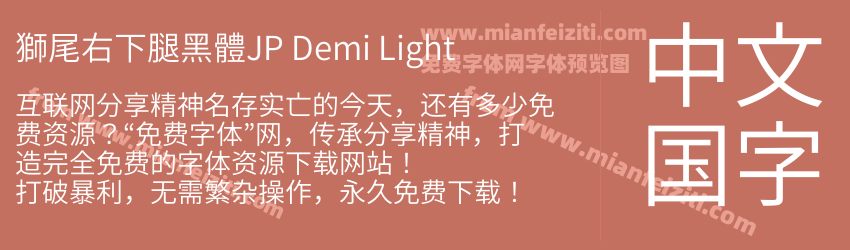
獅尾右下腿黑體JP Demi Light
字体名称: 獅尾右下腿黑體JP Demi Light
Postscript名称: SweiRightBottomLegCJKjp-DemiLight
字体版本: Version 2.130
字体字重: DemiLight
本款“獅尾右下腿黑體JP Demi Light”是一款书写很新颖的字体,字体大方,适合各种设计作品使用!欢迎下载!